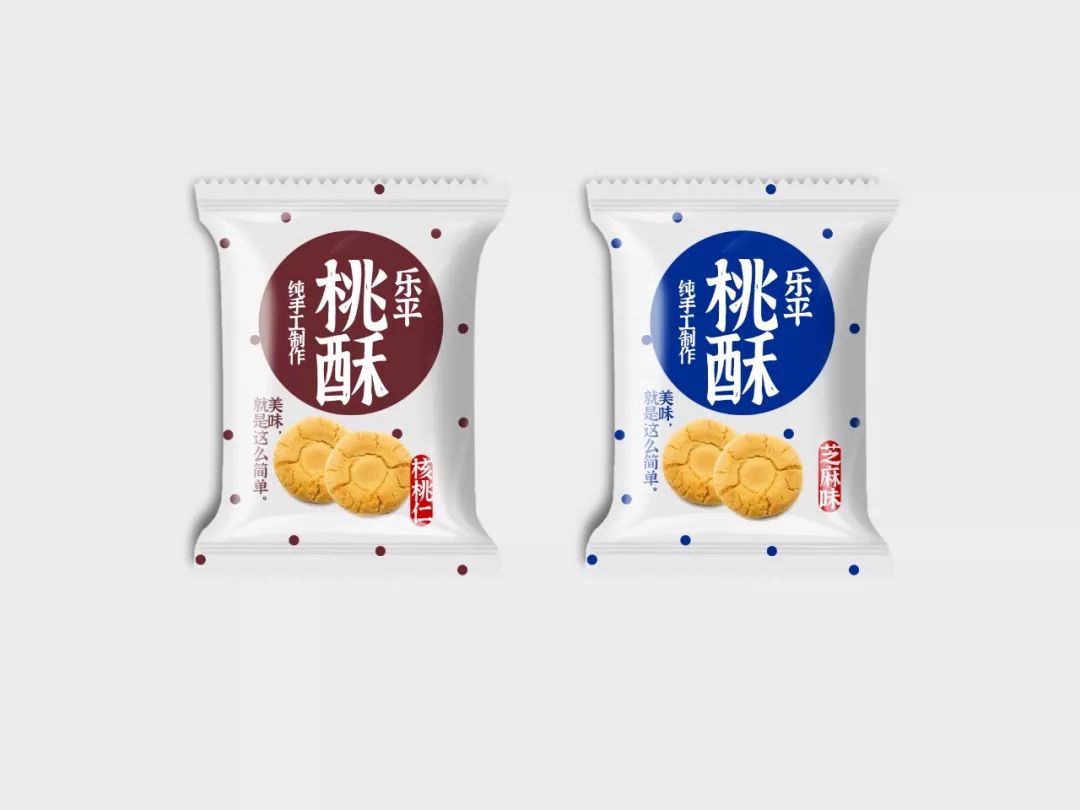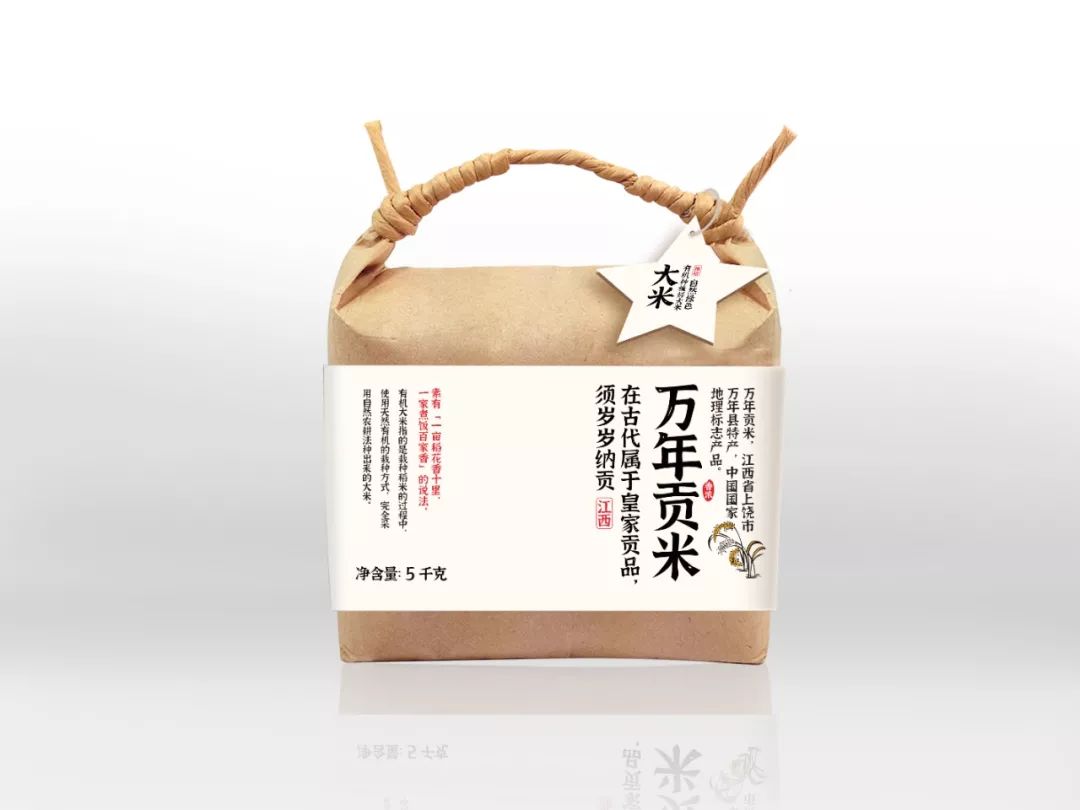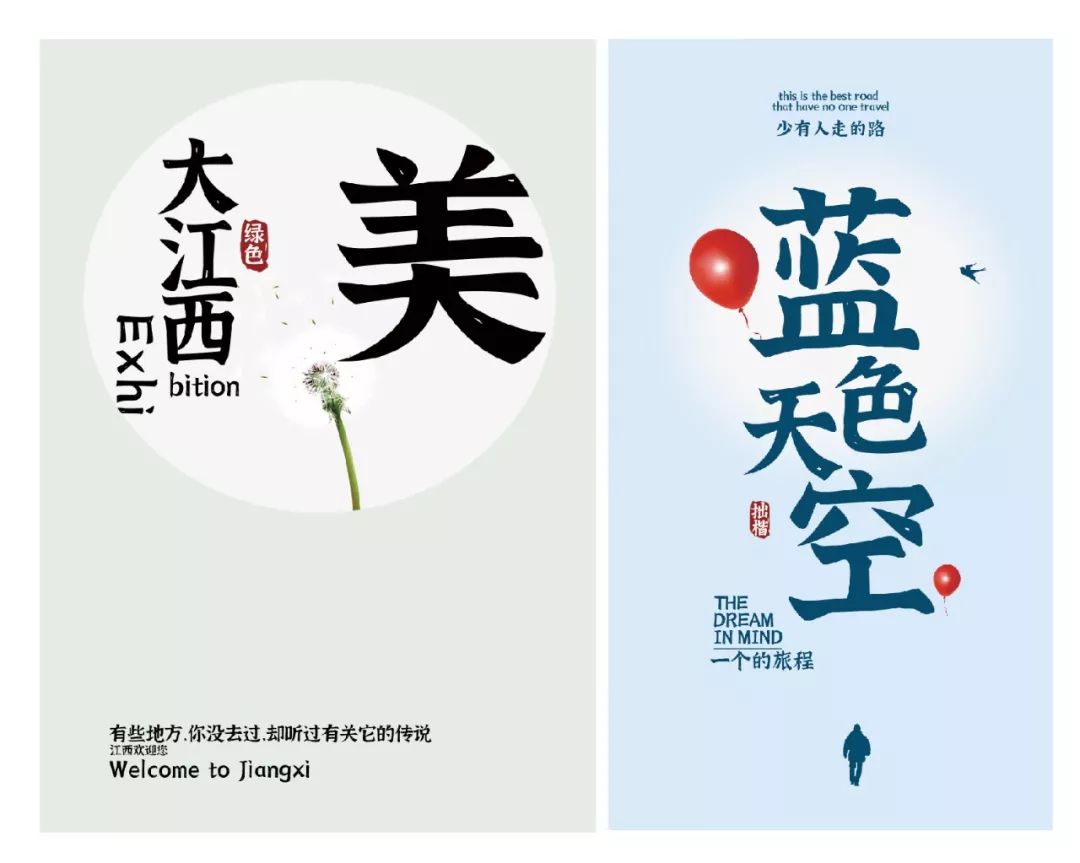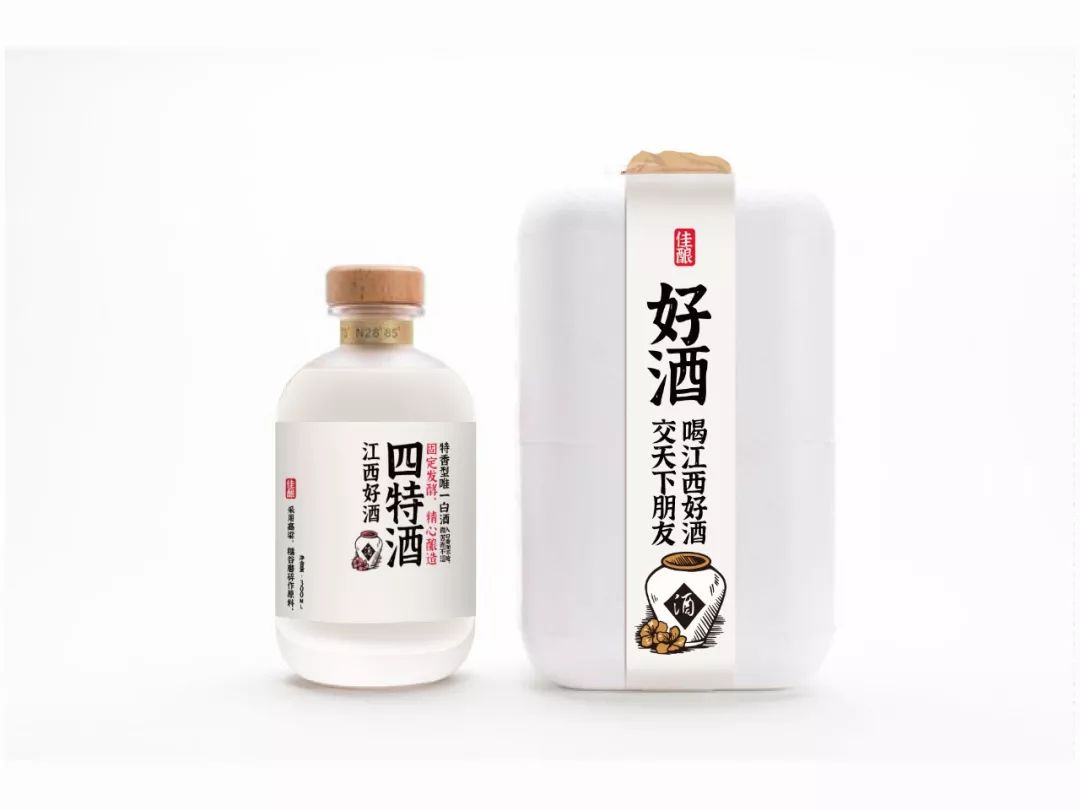
2020年元旦设计师黄煜臣也发布了今年第一套可以免费商用的字体「江西拙楷体」。做一套字体所需要花费的精力和时间是十分巨大的,黄煜臣半年多来夜以继日地辛劳创作才使这套非常漂亮的字体面世。
这是一套手写楷体,相比电脑中标准化制作的楷体,这套字体的笔画会带有一些书写的痕迹,每个字的笔画是没有统一标准的,所以看上去显得不够规范,但是会有一种手写的自然之感。